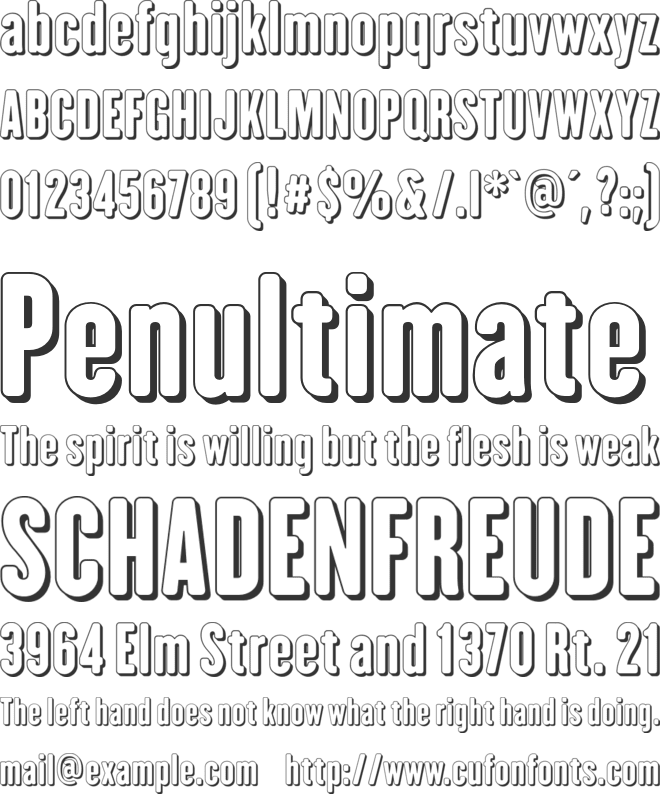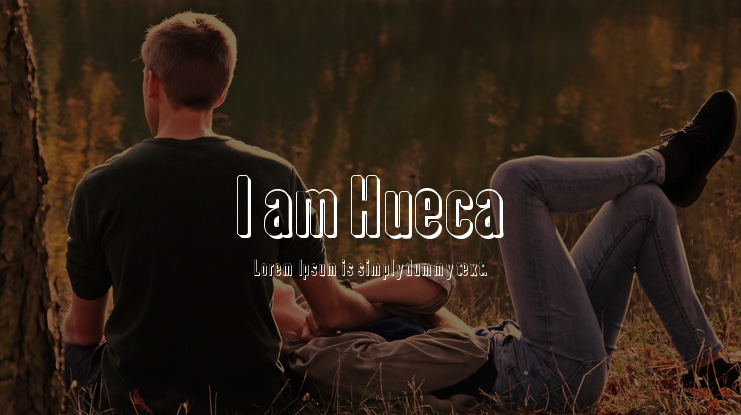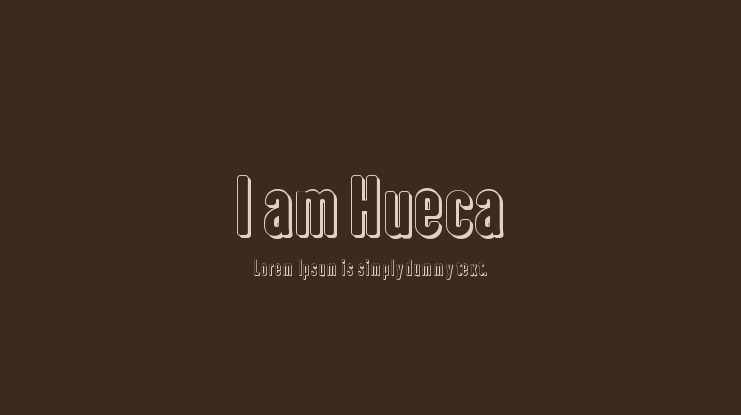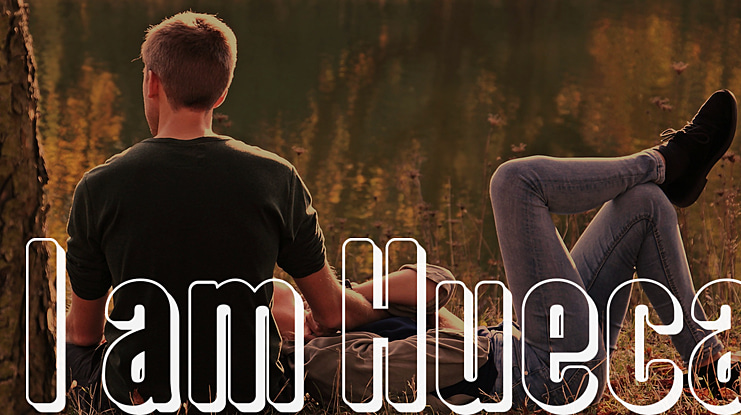
I am Hueca Font
I am Hueca. es una fuente black, comprimida, sans serif y 3D, dispone de 375 glifos para todos los lenguajes derivados del latín.Thank you for your interest in my font :) This font is free for personal & commercial use.